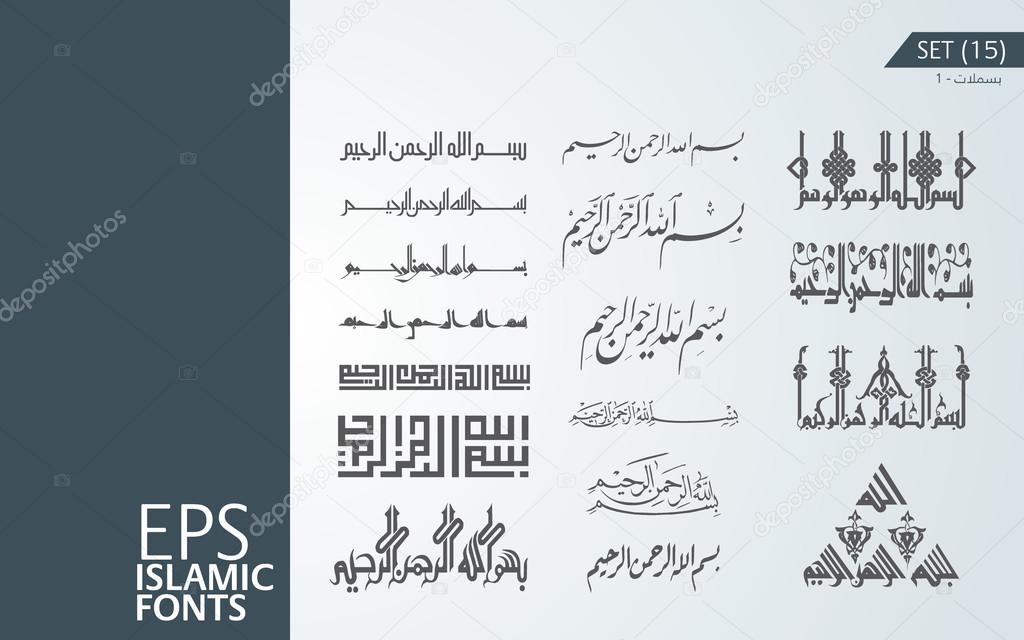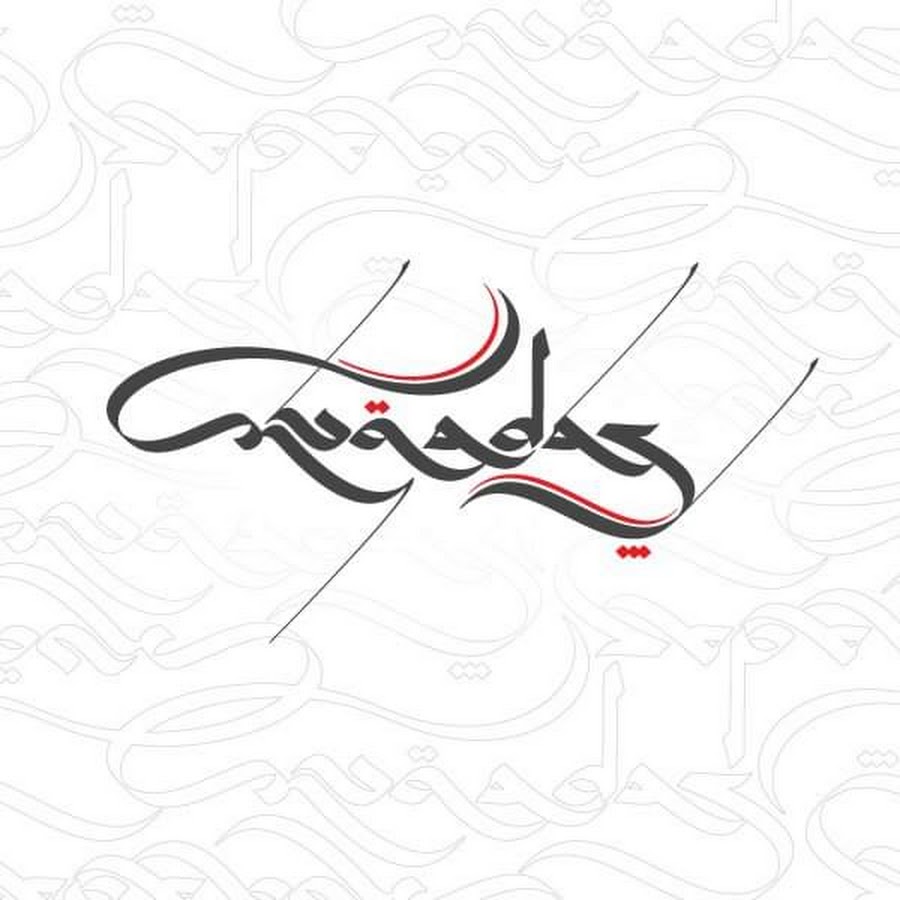
Арабский шрифт — это… Что такое Арабский шрифт?
- Символы арабского алфавита, используемые для набора текста на арабском, персидском, афганском и некоторых других языках народов Азии. Арабский алфавит состоит из 26 согласных букв; гласные обозначаются различными комбинациями точек и черточек над или под согласными буквами. Арабский текст содержит до 100 литер различного начертания; набор с использованием арабского шрифта проводят справа налево; в наборе отсутствуют прописные буквы, знаки препинания и переноса (перенос не допускается).
Корни в истории: понимание каллиграфии рука’а и ее важности
Письмо «рука’а» уже может быть отнесено к истории, однако его уникальные характеристики сделали его наилучшим вариантом при выборе стиля с целью украшения, и сегодня это пример того, как каллиграфическое украшение создало новые способы художественной интерпретации.
В X–XII веках возникла система пропорциональной каллиграфии, в которой выделялись шесть стилей: насх, тулут, мухаккак, райхани, тауки’ и рука’а.
Эта новая кодификация показала, что форма каждой буквы должна определяться определенным количеством ромбических точек и их стандартизированными пропорциями по отношению друг к другу.
Из шести пропорциональных шрифтов, получивших название «Шесть перьев», – рука’а в значительной степени остается историческим.
Именно с этой первоначальной цели стиль и получил свое название: рук’а означает: «заплатка» или «кусок ткани», что указывает на то, как часто он появлялся на небольших по размеру бумагах. Хотя каллиграфы предпочитают использовать его для более декоративных целей, историческое позиционирование стиля рука’а не означает, что это утраченный или забытый текст. Скорее, это пример шрифта, который, благодаря простоте чтения, скорости написания и в то же время достаточной сложности, использовался в эстетических целях.
Основанный на стилях «насх» и «тулут», рук’а был создан во времена хиджры XIII века османами, по утверждению сотружников Музея каллиграфии Шарджи, а также согласно результатам исследователей исламской культуры X века, а имнно Ибн аль-Надима, Аль-Фихриста и Аль-Фадлом ибн Сахля.
Рука’а характеризуется необычными связями букв, которые отсутствуют в других шрифтах, таких как буквы «даль» или «алиф». Меньшая версия тауки’– это шесть пропорциональных шрифтов, которые часто сочетаются с их меньшими или большими аналогами; при этом шрифт рука’а имеет подчеркнуто криволинейные штрихи и нетрадиционные лигатуры с нисходящими петлями, связанными буквами и тенденцией к определенному подъему линии в конце слов, при чередовании с некоторыми из шести других классических или пропорциональных шрифтов.
Обрезанные буквы, состоящие из коротких, прямых линий, простых расцветок и соединения диакритических точек с изолированными буквами, означают явное отсутствие удлинений и необходимости поднимать перо от бумаги, что делает шрифт рука’а эффективным, разборчивым и полезным в каллиграфии для рукописей, нерелигиозных текстов и рассказов либо в частной переписке.